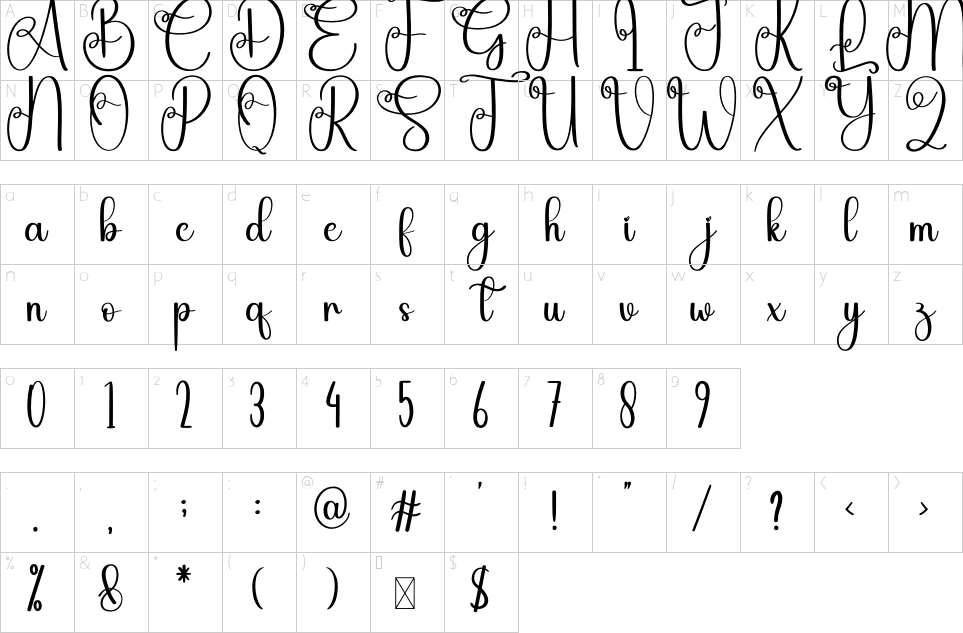
Aqui está uma descrição em português do Brasil para a página de download da fonte ‘Autography Font’, mantendo-se informativo e convidativo, sem inovar na descrição original ou usar markdown: A Autography font oferece um design elegante e moderno, perfeito para qualquer tipo de projeto gráfico. Introduzida por William Jhordy, esta fonte é uma escolha ideal para quem busca um equilíbrio perfeito entre funcionalidade e estética. Com uma fácil leitura e um amplo conjunto de caracteres, Autography é uma ótima escolha para designers gráficos iniciantes e experientes. Se você está procurando uma fonte clássica com um toque moderno, a Autography é uma escolha segura que pode se tornar uma das suas favoritas. Descubra mais sobre esta fonte e baixe-a agora em seu computador Windows ou Mac.